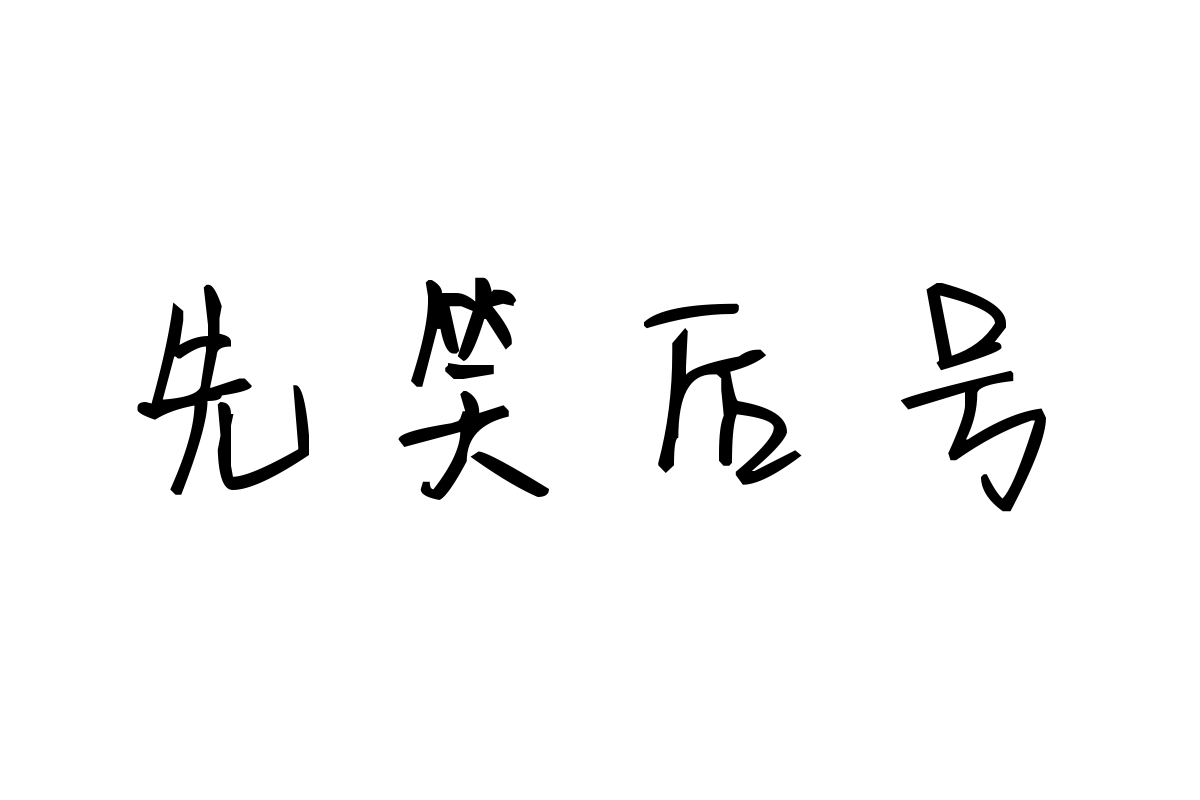
米开花样年华体,是一款具有独特艺术风格的字体。它由著名书法家米开朗基罗(Michelangelo)在15世纪创作,以其独特的线条和结构而闻名。这款字体的设计灵感来自于米开朗基罗的画作,特别是他的《大卫》雕像。
米开花样年华体的字体特点如下:
1. 优雅:这款字体线条流畅,给人一种优雅的感觉。它的曲线和形状都经过精心设计,使得整体看起来非常和谐。
2. 力量:虽然这款字体看起来优雅,但它也具有一种力量感。这是因为米开朗基罗在创作时使用了大胆而有力的线条,使得整个字体看起来非常有力量。
3. 复杂性:米开花样年华体的字体设计非常复杂,包含了许多不同的笔画和形状。这使得这款字体在视觉上非常吸引人,同时也需要较高的审美水平来欣赏。
4. 独特性:由于米开朗基罗的原创性,这款字体在世界上非常罕见。这使得它成为了一种独特的艺术品,值得人们去欣赏和收藏。
总的来说,米开花样年华体是一款非常独特且具有艺术价值的字体。如果你喜欢优雅、力量和复杂性,那么这款字体绝对值得一试。
米开花样年华体